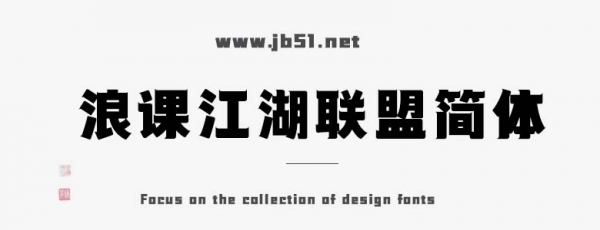
浪課江湖聯(lián)盟簡(jiǎn)體是可免費(fèi)商用的藝術(shù)字體字體,這款字體筆觸適中,字形端正,具有很好的視覺(jué)感,適合應(yīng)用于藝術(shù)設(shè)計(jì)、平面宣傳設(shè)計(jì)、網(wǎng)頁(yè)設(shè)計(jì),書(shū)法字帖等領(lǐng)域,需要的朋友可以前來(lái)本站下載。
「浪課江湖聯(lián)盟簡(jiǎn)體」將復(fù)古感受融入字體筆畫(huà),在標(biāo)題黑體中獨(dú)樹(shù)一幟,大部分筆畫(huà)末端融入尖角外挑,靈感來(lái)自于中國(guó)古建筑的“飛檐”特征,結(jié)構(gòu)轉(zhuǎn)角采用非正圓倒角的方式,增加人文無(wú)襯線設(shè)計(jì)感,簡(jiǎn)約而別致。
「浪課江湖聯(lián)盟簡(jiǎn)體」吸取傳統(tǒng)字體審美,采用橫細(xì)豎粗的筆畫(huà)寬度比,橫豎筆畫(huà)上,常規(guī)豎筆畫(huà)的寬度約為常規(guī)橫筆畫(huà)寬度的1.35倍(A:B=1:1.35),筆畫(huà)書(shū)寫(xiě)特征借鑒傳統(tǒng)書(shū)法體行筆規(guī)范,這就有了每個(gè)小尖角的出現(xiàn)。
「浪課江湖聯(lián)盟簡(jiǎn)體」中的豎橫勾處理方式為避免復(fù)雜,勾末端不加尖角。顛覆了傳統(tǒng)的“向橫處加厚”,轉(zhuǎn)橫后與常規(guī)橫保持統(tǒng)一粗細(xì),勾傾斜時(shí)厚度兩側(cè)保持傾斜角統(tǒng)一,延續(xù)傳統(tǒng)但融入現(xiàn)代感。
「浪課江湖聯(lián)盟簡(jiǎn)體」中的豎勾是在豎橫勾的基礎(chǔ)上簡(jiǎn)化得到,讓勾筆畫(huà)有橫向延伸感后加入非正圓倒角尾勾,讓勾的完成更自然。
「浪課江湖聯(lián)盟簡(jiǎn)體」筆畫(huà)厚實(shí),撇捺提點(diǎn)等筆畫(huà)以人文無(wú)襯線原則曲線繪制,大部分筆畫(huà)轉(zhuǎn)角以正圓倒角做視覺(jué)柔化處理。
「浪課江湖聯(lián)盟簡(jiǎn)體」比例接近正方形字面,但寬度比例大于高度比例,字體視覺(jué)重心較為平穩(wěn),正負(fù)形分布力量感均衡,適用于標(biāo)題或副標(biāo)題層級(jí)。
「浪課江湖聯(lián)盟簡(jiǎn)體」字面設(shè)計(jì)考慮到傳統(tǒng)漢字結(jié)構(gòu)特征,字面呈現(xiàn)高度方塊化特征,字體中宮緊湊、灰度均衡,作為標(biāo)題體有著較高的辨識(shí)度。